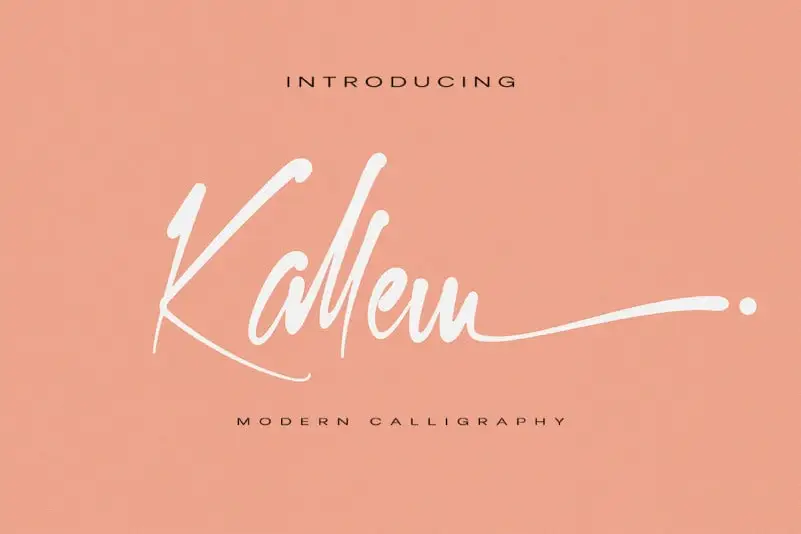
Kallem Script Font – Download Grátis
A fonte ‘Kallem Script Font’ é uma elegante tipografia moderna com traços únicos que traz a sensação mágica do contato dos dedos na tinta. Ideal para criar assinaturas de logotipo, marcas d’água em estúdios fotográficos ou convites de casamento, ela se torna perfeita para um novo sinalizador de marca ou assinatura inicial. Esta fonte é uma opção perfeita para designers e criadores de conteúdo que desejam dar um toque único a seus projetos, seja em elementos visuais como logotipos, signatarias ou trabalhos artísticos digitais. Com suas linhas suaves e expressivas, ‘Kallem Script Font’ adiciona um charme sofisticado a qualquer projeto. Não perca essa oportunidade de adicionar uma nova dimensão ao seu trabalho com esta fonte única do designer khaiuns.